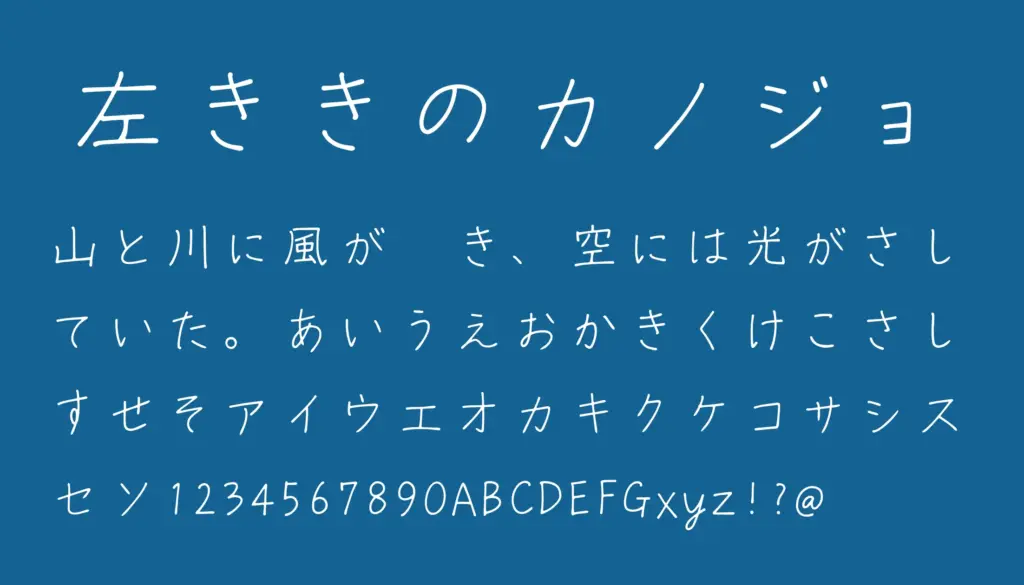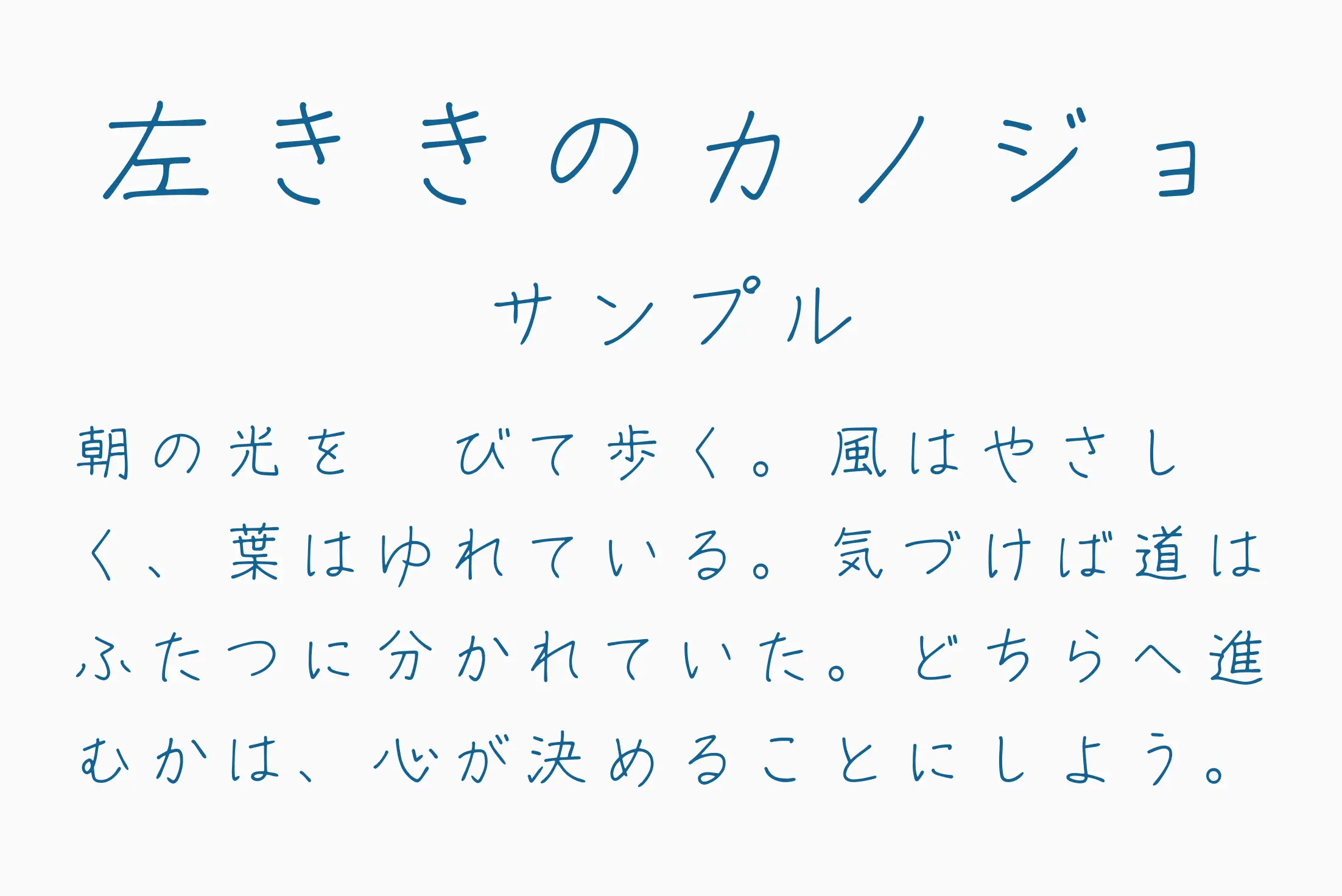
手書き風の優しいタッチが特徴の日本語フリーフォントです。文字の線はやや不揃いで、自然な揺らぎを感じさせるデザインが魅力。名前の通り、左利きの人が書いたような個性ある筆致で、柔らかく温かみのある雰囲気を演出します。ブログのタイトル、日常系イラスト、手紙風のデザインなど、カジュアルで親しみやすい場面に最適。
左利きの彼女